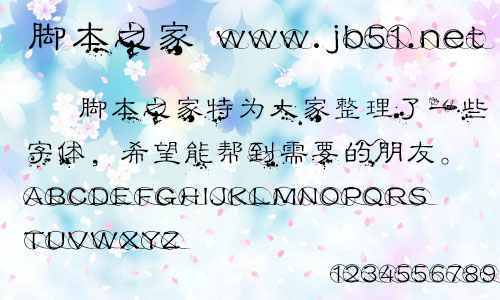
墨香古意字體是一款古色古香的中文藝術(shù)字體,擁有潑墨式的字體風(fēng)格,整體看起來就像一副水墨畫一樣美麗,將藝術(shù)與字體完美融合,同時(shí)還不影響漢字識(shí)別度,能夠給閱讀者帶來更強(qiáng)的沖擊力和記憶程度,比較適合網(wǎng)站字體、雜志封面、廣告設(shè)計(jì)等使用。需要的朋友可以前來本站下載。